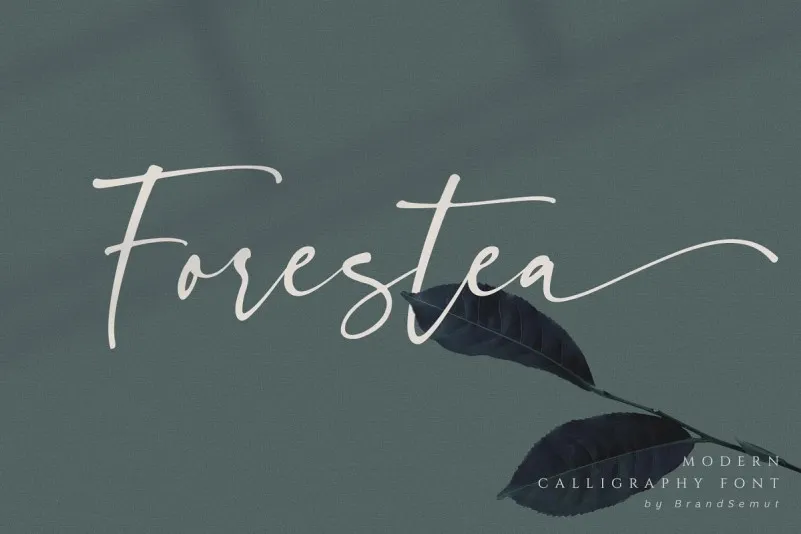
Forestea Font – Fonte Grátis
Forestea Font
A ‘Forestea Font’ é uma maravilha de tipo script que oferece um toque moderno e sofisticado, perfeito para qualquer projeto gráfico. Desenvolvida pelo designer BrandSemut, essa fonte apresenta um acabamento suave e textura delicada que complementa perfeitamente a sua obra. Com recursos OpenType como ligaturas e alternativas, o ‘Forestea Font’ se destaca entre as demais. Além disso, oferece números, pontuação e apoio para várias línguas, tornando-o extremamente versátil. Seus detalhes finos e seus movimentos fluidos permitem que você trabalhe em diversas técnicas de impressão, desde a costura até o corte laser ou até mesmo a gravação dourada. Seja qual for seu projeto, essa fonte é um excelente aliado para alcançar resultados incríveis.